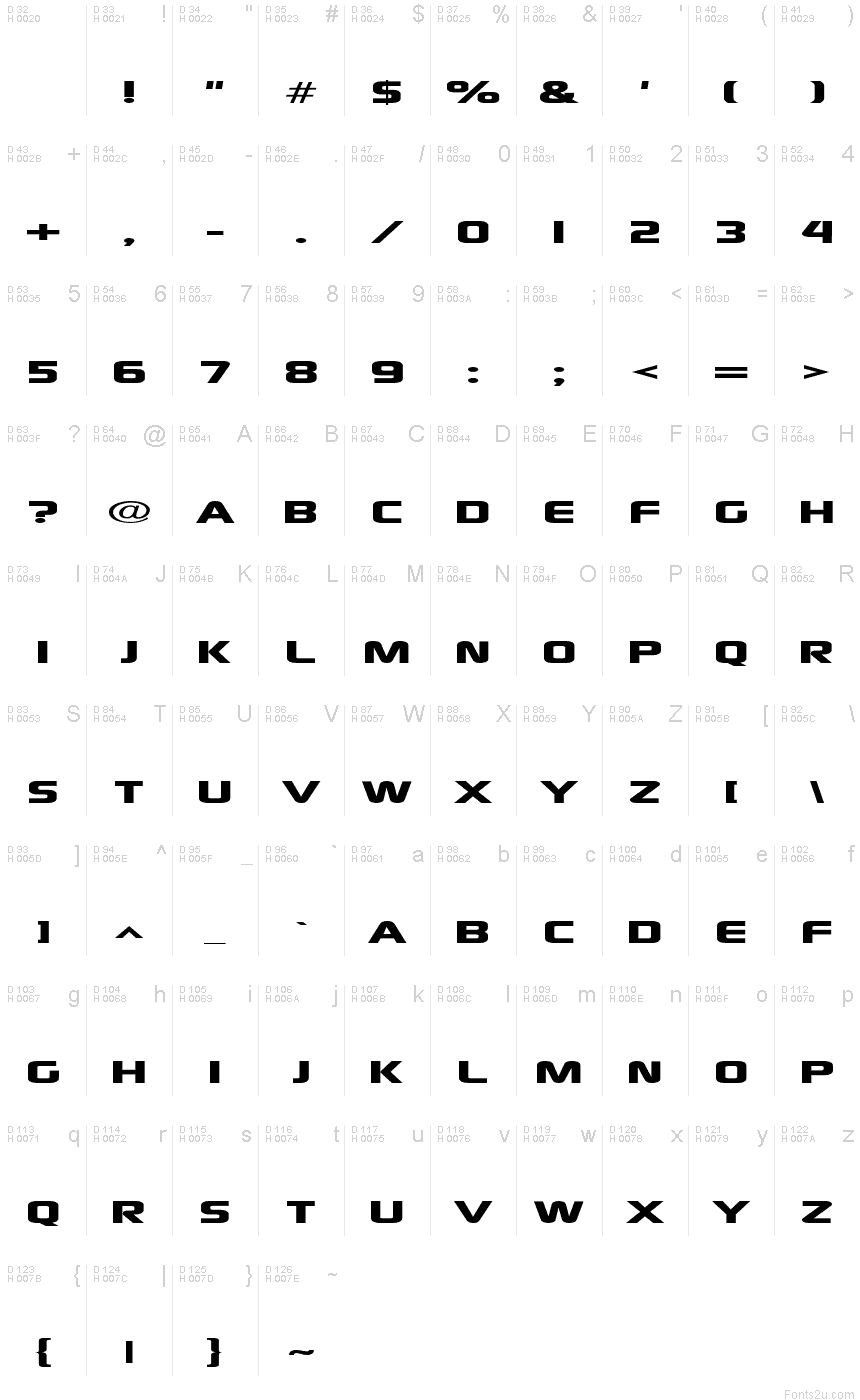
Xscale von Designsalon ist eine kostenlose, moderne Techno-Display-Schrift mit breiten, kantigen Großbuchstaben und einer reduzierten, dynamischen Anmutung. Die Buchstaben bestehen aus massiven Strichen, gekappten Kurven und diagonalen Schnitten, was das Gesamtbild schnell, kompakt und industriell wirken lässt – ohne überladen zu sein.
Sie eignet sich perfekt für Anwendungen, bei denen der Titel die visuelle Hauptrolle spielt: Poster, Albumcover, Gaming-Grafiken, Tech-Branding und Event-Flyer harmonieren hervorragend mit ihrer markanten Energie. Als kostenlose Schrift funktioniert Xscale zudem bestens für kurze Schlagzeilen, Titelkarten und Monogramme, da die Großbuchstaben schnell ineinandergreifen und kräftige, grafische Formen bilden.